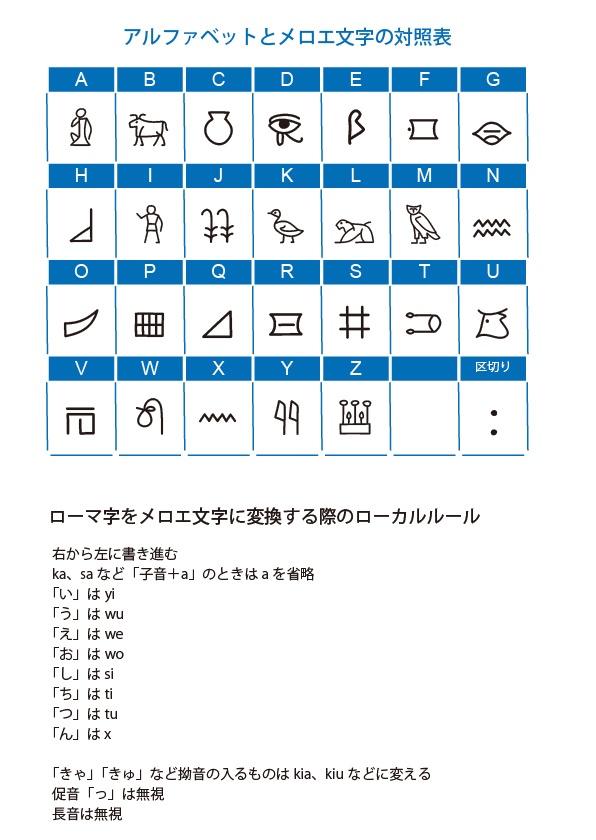
古代エジプトの近くにあったクシュ王国、メロエ王国で使われていたメロエ文字のフォントです。 メロエ文字は、文字の形はヒエログリフを借用していますが、使い方はかなり異なりアルファベットに近いものでした。ただし子音の発音については、他の母音の表記がない場合は母音aが含まれ、アブギダと呼ばれる文字体系に分類されます。 全23字の文字をアルファベットにあてはめました。ただし一部の文字については本来の発音とは違うアルファベットに当てはめています。これについては既存のメロエ文字のフォントに準拠しました。 また、メロエ文字を当てはめなかった3文字(f、h、x)については、メロエ文字r、q、nの異体字をそれぞれあてはめています。 【収録文字】 英語アルファベットa〜z、A〜Z(大文字小文字とも同じメロエ文字をあてはめています)。:(メロエ文字の区切り記号をあてはめています)。 【データ内容・使用方法】 zipファイルを解凍してください。 TTFファイル meroiticfonta.ttf JPGファイル(アルファベットとメロエ文字の対照表) meroitic.jpg テキストファイル(このファイル) readme.txt が収録されています。 meroiticfonta.ttfをインストールしてください。 【購入の際の注意点】 商用利用OKです。 使用した場合、ご一報いただけるとうれしいです。Twitterなどで紹介します。 フォントファイルの改変・再配布は禁止です。